ブラウザのフォント
私が常用しているブラウザはNetscpe Navigator 3.0 Goldで、OSはWindows95である。画面の設定は、17インチモニタで1280x1024とし、ブラウザのフォント設定は「Proportional Font:MS P明朝」「Fixed Font:MS明朝」である。
しかし、これは日本語の文章が大変見づらい。何故かというと行間が詰まりすぎるのである。どんな感じになるかは次のとおり。
では英語(アルファベット)はというと、
スッキリしている。
何故こんなことになるのか、素人なりに見てみると。
拡大してみる
上の文字を拡大し、日本語、英語とも同じ位置に基準線を引いてみる。
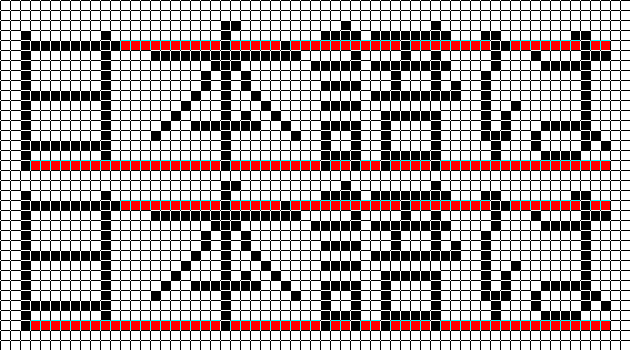
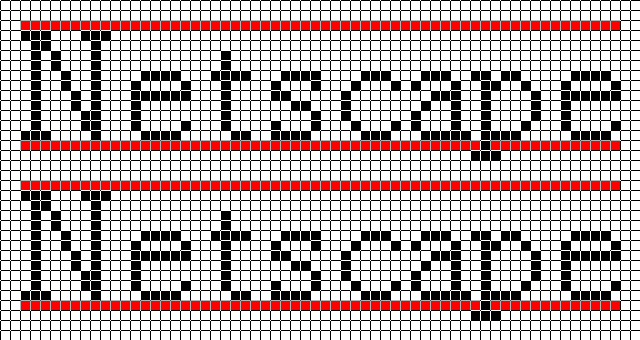
見てみると、
「日本語/漢字」:上3コマ、下1コマのオーバー
「日本語/ひらがな」:上2コマ、下オーバー無し
「英語」:上オーバー無し、下J,g,j,p,q,yのみ2コマオーバー
これでは見づらいわけである。
ちなみに数字は次のようになります。
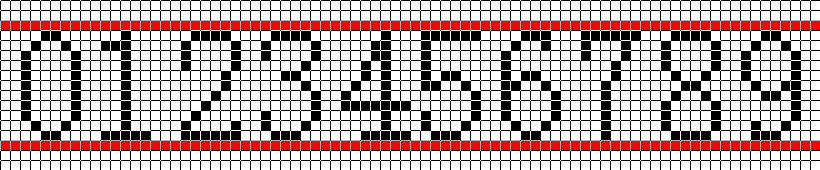
Macは見やすい
ちなみに、Macでは「Osaka」というフォントがあり、これを使うと同じNetscapeでも行間が適度に空いて見やすいという話を聞いたので、早速Mac使いの友人に見せてもらうとホントである。文字自体の雰囲気も優しい感じであるが、とにかく行間が全然違う。見やすい。インターネットが主な目的でパソコンを使うならMacを奨めたくなってしまう。
ブラウザ専用フォントが欲しい
これからは、「スタイルシート」とかも標準になるらしいが、今までのコンテンツもあるし、上の基準線の上下または、せめて下にははみ出さない「ブラウザ専用フォント」なんて何処かで作ってないかなぁ。インターネット、ブラウザ、そしてパソコン自体、元は英語圏の文化だから、日本語みたいなのは優先順位が低いのかもしれないけど、せめてユーザの使い勝手を大きく左右するフォントぐらいは「ジャパンオリジナル」なものがあったらと思います。
ジャストシステムあたり、評価の高いATOKに加え、さらに「ブラウザでも見やすいフォント」なんて作ったら、もうWordなんて誰も使わなくなるんじゃないかなぁ(これは言い過ぎ)。最近一太郎押され気味だし。やっぱり日本語するならジャストシステムだ!一太郎だ!!って起死回生の一発。売れると思うんだけど。まあ、マイクロソフトでもいいけど。
他の人のWebページでもたまにこの話題見かけます。で、色々工夫というか裏技みたいなのやってますが、決め手に欠けますねぇ。